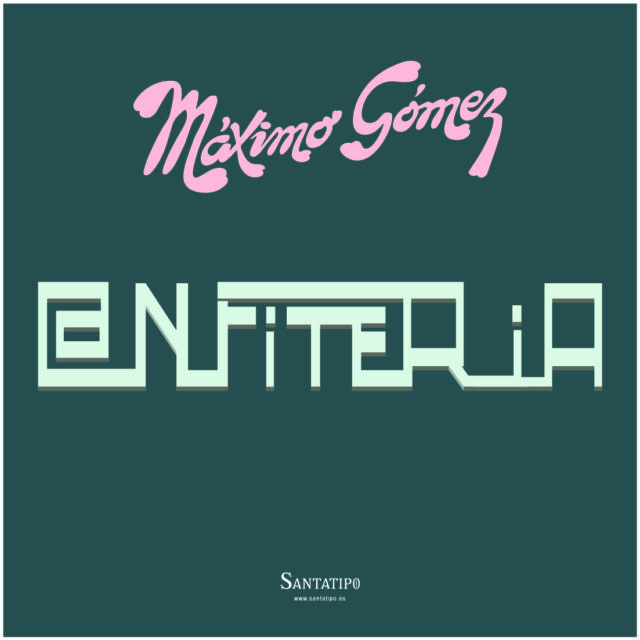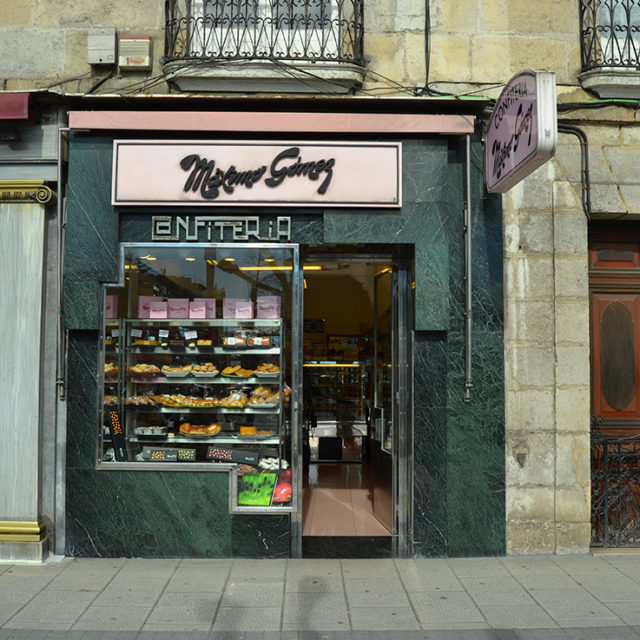
Confitería Máximo Gómez
En el Paseo Pereda, 7, había un pequeño despacho de una de las confiterías más conocidas de la ciudad. Máximo Gómez.
Un diseño único donde su característica fachada de marmol verde, de mediados de siglo, con su escaparate, formaban un juego visual geométrico que se remataba con el rótulo de metal formado por esa tipografía geométrica.
En la segunda década de los 2000 comenzó el cierre de todos los locales. Este estuvo hasta el año 2016-2017 intacto, cuando fue objeto de reforma para incorporarse como una ampliación a la joyería vecina de Bayanne.
El rótulo fue desmontado y está custodiado por la familia.